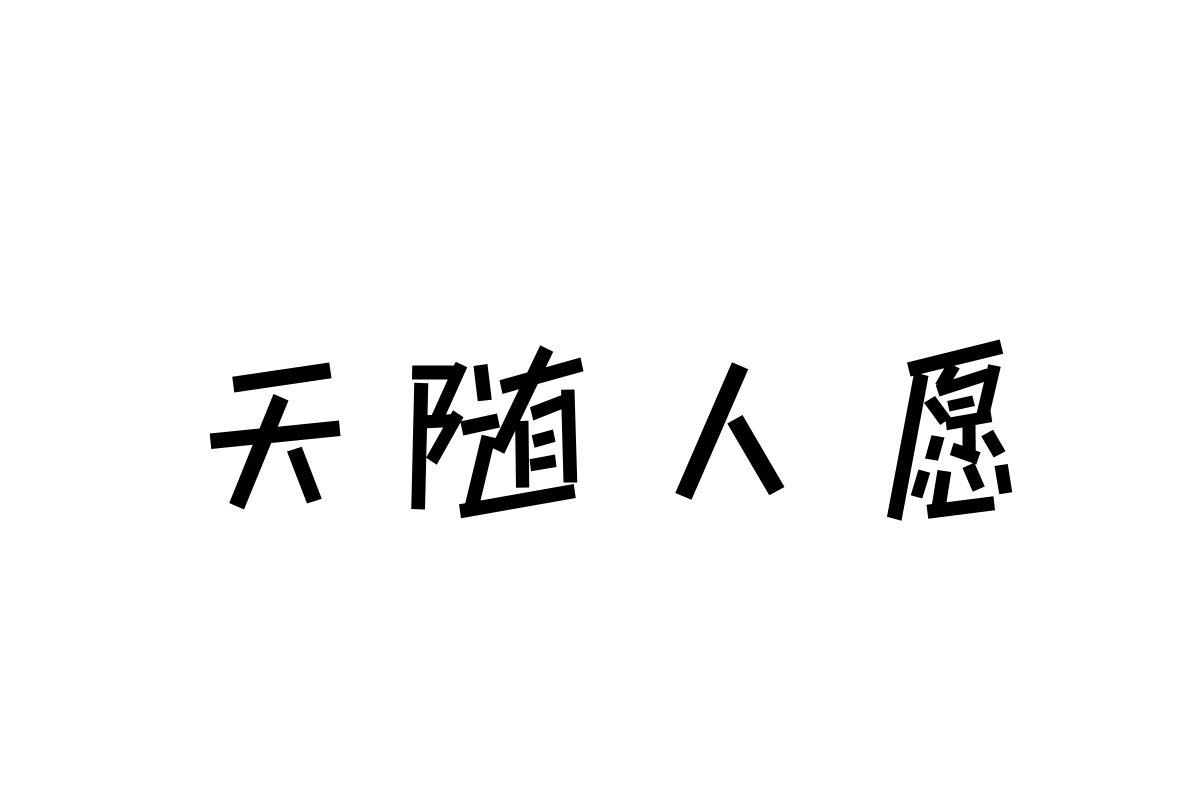
三极玩趣简体中粗字体是专为中文用户设计的字体,具有以下特点:
1. 设计风格:三极玩趣简体中粗字体采用现代简约风格,线条流畅,字形饱满,适合用于各种设计场景。
2. 字重选择:该字体提供多种字重选择,包括粗体、中粗体和细体等,满足不同设计需求。
3. 字符间距:三极玩趣简体中粗字体支持多种字符间距设置,如常规、宽松、紧凑等,以适应不同的排版需求。
6. 应用场景:三极玩趣简体中粗字体适用于广告设计、包装设计、网页设计、PPT制作等多种设计场景。